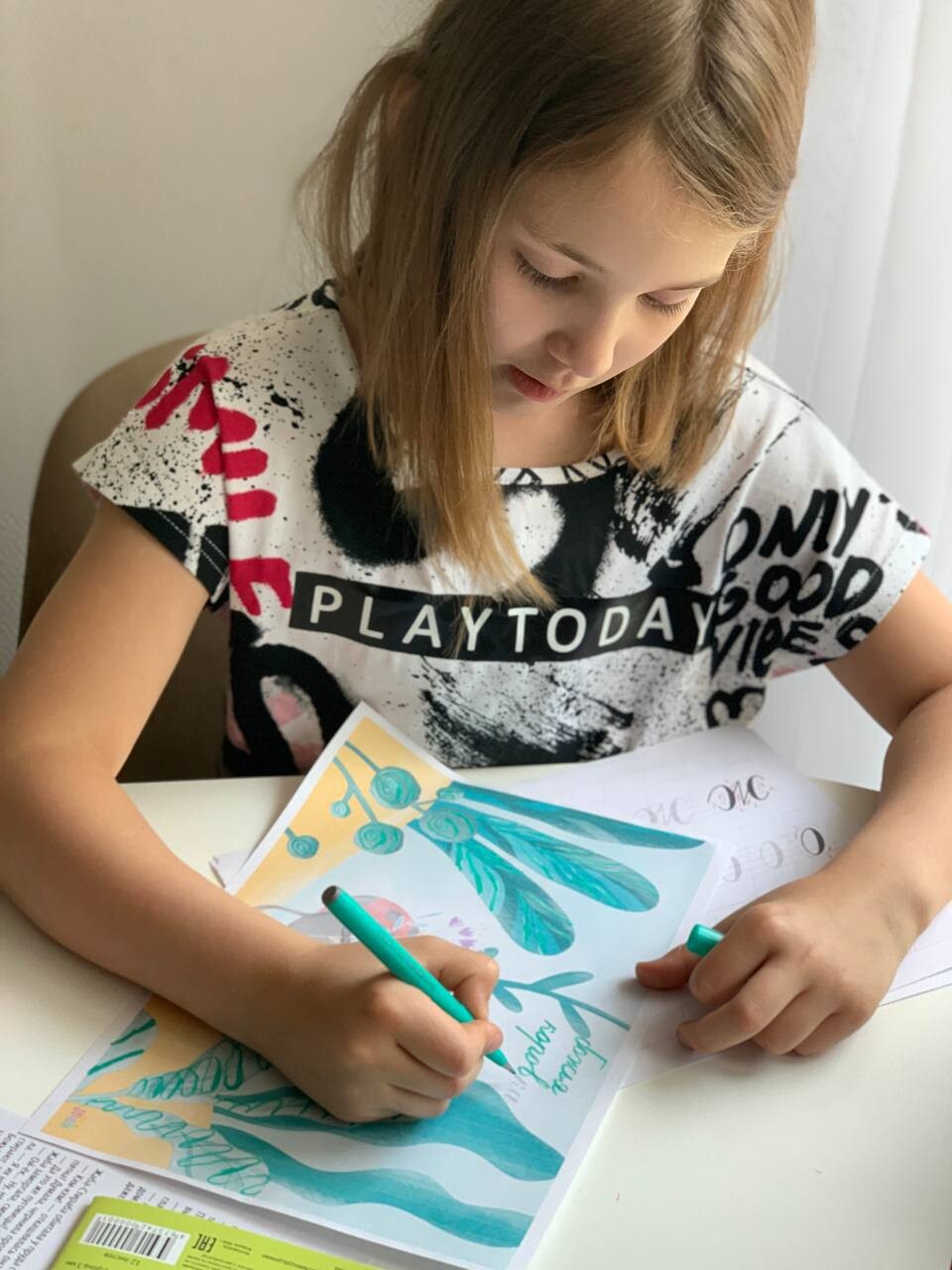
Коррекция без слез: как спасти плохой почерк у ребенка в младшей школе
В возрасте 7–9 лет, во 2–3 классе, проблемы с письмом становятся настоящей «зубной болью». Объем заданий растет, скорость письма ребенка увеличивается, и накопленные ошибки «взрываются» неразборчивостью.
Часто почерк ухудшается во 2 классе: ребенок злится, мама расстраивается — возникает классическая ситуация «Я не могу и не хочу».
Почему ребенок пишет неразборчиво и почему обычные прописи для исправления почерка не помогают
Часто родители заставляют ребенка переписывать текст по три раза. Но такое исправление почерка лишь закрепляет ошибку и снижает мотивацию к учебе.
Если рука зажата, а буквы пишутся не в ту сторону, ребенок просто трижды повторяет неправильное движение. Чтобы действительно улучшить почерк, нужно вернуться на два шага назад.
Обычное механическое повторение в тетрадях бессильно.
Как улучшить почерк ребенка: эффективная методика «Игра в каллиграфию»
Алгоритм обучения каллиграфии для детей строится на трех шагах.
1. Снятие зажима
В 7–9 лет ребенок уже привык «давить» на ручку. Мы меняем инструмент на брашпен или аквабраш — кисть для письма.
Когда соблюдается правильная посадка при письме и внедряется методика лёгкого хвата, рука наконец чувствует:
«О, так мне легче. Я понимаю, что я делаю».
2. Работа с «Золотым овалом»
60% букв русского алфавита содержат одинаковую фигуру — овал.
Если пройти целевые уроки чистописания и научить ребенка писать букву О и всю овальную группу правильно, против часовой стрелки, это автоматически улучшит написание еще 16 букв.
Это единая логика, которую дает курс по каллиграфии в игровой форме, экономя ресурс мозга ребенка.
3. Мотивация через успех
В младшей школе ребенку важно видеть результат.
Мы уходим от скучных прописей к игре в каллиграфию для детей, где письмо становится частью творчества.
Исправление почерка за месяц или даже за неделю — это не муштра, а переобучение руки и правильной траектории движения. Такая коррекция почерка у ребенка возможна при регулярной, но радостной практике.